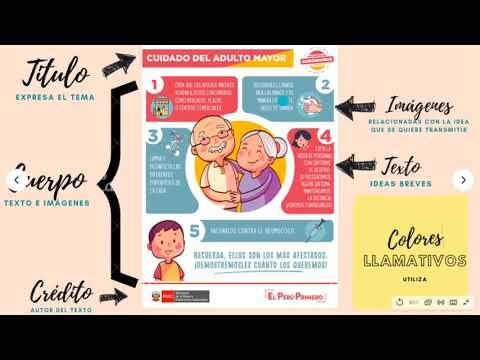
La Relevancia de la Tipografía en Infografías
La tipografía juega un papel fundamental en la efectividad de las infografías, ya que no solo transmite información, sino que también influye en la percepción y el entendimiento del mensaje. Elegir el tipo de letra adecuado puede realzar la claridad, la estética y la jerarquía visual, guiando al espectador a través de los datos presentados. En un mundo saturado de información, la importancia de la tipografía en las infografías se convierte en un elemento clave para captar la atención y facilitar la comprensión de contenidos complejos.
¿Cuál es el impacto de la tipografía en infografías?
La tipografía en infografías es importante; mejora la legibilidad, destaca información clave y establece el tono visual, facilitando la comprensión del contenido.
¿Qué significa tipografía en el contexto de las infografías?
La tipografía en las infografías es un elemento clave que convierte el texto en un componente visual atractivo y resaltante. A través de un cuidadoso proceso de diseño, se seleccionan y disponen diferentes tipografías en un espacio determinado, transformando las palabras en imágenes que comunican información de manera valiosa. La estructura resultante variará según el contexto de la publicación, asegurando que cada infografía no solo sea estética, sino también funcional y fácil de comprender.
¿Cuál es la relevancia de la tipografía?
La tipografía es un elemento importante en la comunicación visual, ya que no solo se trata de letras, sino de cómo estas se presentan para transmitir un mensaje de manera valiosa. A través de la cuidadosa elección de características como la forma, el espaciado, el color y el grosor, la tipografía puede realzar el significado del contenido, captar la atención del lector y evocar emociones. De esta manera, una buena tipografía no solo comunica información, sino que también enriquece la experiencia del lector, convirtiéndose en un arte que conecta lo escrito con lo visual.
¿Cuál es la función del texto escrito en la infografía?
El texto escrito en una infografía cumple una función fundamental al ofrecer al lector una explicación clara y concisa que complementa la información visual. Mientras que el cuerpo visual presenta datos a través de gráficos, mapas o diagramas, el texto proporciona el contexto necesario para que el mensaje sea plenamente comprendido. De esta manera, ambos elementos trabajan en conjunto, asegurando que la información sea accesible y fácil de interpretar para el público.
Impacto Visual: La Clave del Mensaje
La comunicación valiosa no solo se basa en las palabras que elegimos, sino también en cómo las presentamos visualmente. Un diseño atractivo y bien estructurado puede captar la atención del público y facilitar la comprensión del mensaje. Los elementos visuales, como imágenes, gráficos y colores, juegan un papel importante en la transmisión de ideas, ya que generan emociones y refuerzan la información escrita. Al integrar un impacto visual contundente, aumentamos la probabilidad de que nuestro mensaje resuene y perdure en la mente de quienes lo reciben.
Tipografía: El Arte de Comunicar Efectivamente
La tipografía es mucho más que una simple elección de fuentes; es el arte de comunicar de manera valiosa y estética. Cada letra, cada espacio y cada estilo tipográfico contribuyen a la percepción del mensaje que se desea transmitir. Al seleccionar cuidadosamente la tipografía, los diseñadores pueden evocar emociones, establecer jerarquías y guiar la atención del lector, convirtiendo un texto ordinario en una experiencia visual cautivadora.
Además, la tipografía juega un papel importante en la legibilidad y la accesibilidad de un mensaje. Una buena elección tipográfica facilita la comprensión del contenido, consintiendo que la audiencia se sumerja en la información sin distracciones. La combinación adecuada de tamaño, color y estilo puede hacer que un mensaje resalte y sea memorable, asegurando que la comunicación sea valiosa en diversas plataformas y dispositivos.
Por último, la tipografía refleja la identidad y los valores de una marca o proyecto. La coherencia en el uso de tipografías no solo refuerza la imagen visual, sino que también establece una conexión emocional con el público. En un mundo saturado de información, una tipografía bien elegida se convierte en una herramienta poderosa para destacar y dejar una impresión duradera.
Más Allá de las Letras: Diseño y Percepción
El diseño va más allá de la mera estética; se convierte en un lenguaje que comunica y evoca emociones. Cada forma, color y tipografía tiene un impacto profundo en la percepción del mensaje. En un mundo saturado de información, un diseño efectivo no solo atrae la atención, sino que también guía al espectador hacia una comprensión más profunda del contenido. La armonía entre estos elementos es clave para crear experiencias memorables que resuenen con el público.
La percepción juega un papel importante en cómo interpretamos el diseño. Desde la elección de colores hasta la disposición de los elementos visuales, cada decisión puede influir en la forma en que un mensaje es recibido. Los diseñadores deben considerar no solo la intención detrás de su trabajo, sino también cómo las audiencias diversas pueden percibir sus creaciones. La empatía y la investigación son herramientas esenciales para conectar con diferentes grupos demográficos y asegurar que el mensaje se transmita de manera valiosa.